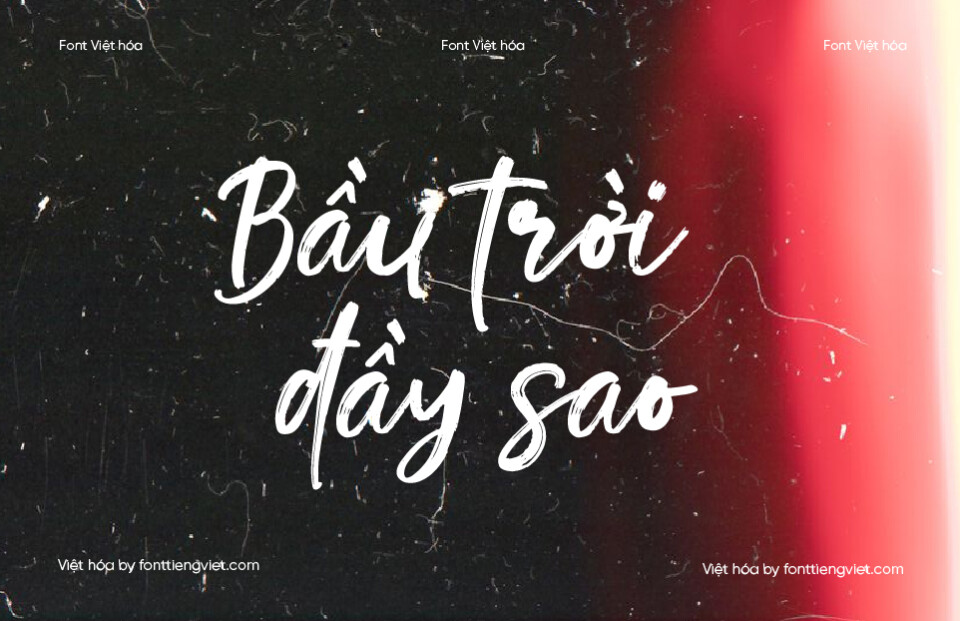
Tải Font Việt hóa 1FTV VIP Doughty Brush: Tuyệt Phẩm Typography Cho Mọi Thiết Kế
Trong thế giới thiết kế đồ họa, việc lựa chọn một Font Chữ phù hợp có thể tạo nên sự khác biệt lớn. Hôm nay, chúng ta sẽ khám phá một “tuyệt phẩm” được cộng đồng designer săn đón: Font Việt hóa 1FTV VIP Doughty Brush. Đây không chỉ là một font cọ nét thông thường, mà còn là sự kết hợp hoàn hảo giữa tính nghệ thuật và khả năng ứng dụng cao, đặc biệt khi đã được Việt hóa. Với sự tỉ mỉ trong từng nét chữ, font này hứa hẹn sẽ là công cụ đắc lực giúp học sinh, sinh viên và các nhà thiết kế tạo ra những ấn phẩm vượt trội, từ đồ án tốt nghiệp cho đến các dự án thương mại.
Khám Phá Sức Hút Đặc Biệt Của Font Việt hóa 1FTV VIP Doughty Brush
Doughty Brush là một kiểu chữ script (chữ viết tay) mang phong cách cọ nét mạnh mẽ và cá tính. Bản gốc của font này đã rất được yêu thích nhờ vào các đường nét tự nhiên, mô phỏng chân thực cảm giác viết bằng cọ mực. Tuy nhiên, đối với người dùng Việt Nam, vấn đề lớn nhất luôn là thiếu ký tự tiếng Việt. Phiên bản 1FTV VIP Doughty Brush đã giải quyết triệt để vấn đề này.
Quá trình “Việt hóa” không chỉ đơn thuần là thêm dấu mà còn là việc tinh chỉnh khoảng cách, kerning và các ký tự đặc biệt (glyphs) để đảm bảo sự liền mạch, hài hòa khi gõ tiếng Việt, từ đó giúp các bạn học sinh, sinh viên dễ dàng tạo ra các bài thuyết trình hay đồ án tốt nghiệp ấn tượng hơn. Sự chuyên nghiệp trong quá trình Việt hóa đã biến Doughty Brush thành một công cụ không thể thiếu trong bộ sưu tập font chữ cao cấp. Chất lượng font chữ này được đánh giá tương đương với các font chữ quốc tế, nhưng lại hoàn toàn tối ưu cho ngôn ngữ mẹ đẻ.
Thiết Kế Đồ Họa Đỉnh Cao Với Phong Cách Brush Art
Font Brush, hay còn gọi là font cọ, là lựa chọn hàng đầu cho những dự án cần sự năng động, sáng tạo và cảm xúc mạnh mẽ. Doughty Brush nổi bật với sự kết hợp giữa nét dày và nét mỏng, tạo ra độ tương phản ấn tượng, thích hợp cho việc thiết kế logo, poster phim, bìa sách hoặc các ấn phẩm quảng cáo. Typography cọ nét này mang lại cảm giác chân thực như một tác phẩm nghệ thuật được vẽ tay, giúp thông điệp truyền tải trở nên gần gũi và cá nhân hơn. Đối với các bạn học sinh chuẩn bị các dự án kỷ yếu hoặc thiết kế áo lớp, việc sử dụng Doughty Brush có thể thổi hồn vào sản phẩm, biến chúng thành những kỷ niệm độc đáo. Font chữ này đặc biệt hữu ích trong các thiết kế liên quan đến nghệ thuật và cảm hứng, nơi mà tính cá nhân được đặt lên hàng đầu.
Tại Sao Font Doughty Brush Việt Hóa Lại Cần Thiết Cho Học Sinh và Sinh Viên?
Để tận dụng tối đa tính năng của Font Việt hóa 1FTV VIP Doughty Brush, bạn cần một số kiến thức cơ bản về phần mềm thiết kế như Adobe Photoshop hoặc Illustrator. Font cọ nét này thường chứa các glyphs (ký tự thay thế) phong phú, cho phép designer tùy chỉnh chữ viết để tạo ra sự khác biệt. Việc khám phá các glyphs này thông qua bảng Character Map sẽ mở ra vô số khả năng sáng tạo, từ việc thay đổi kiểu đầu và cuối chữ cái cho đến việc thêm các nét kéo dài nghệ thuật, làm tăng giá trị thẩm mỹ của sản phẩm cuối cùng.
Cấu Trúc Font và Khả Năng Tương Thích Rộng Rãi
Font Doughty Brush thường được cung cấp ở định dạng OpenType (.otf) hoặc TrueType (.ttf), đảm bảo khả năng tương thích cao với hầu hết các hệ điều hành (Windows, macOS) và các ứng dụng thiết kế phổ biến. Nhờ công nghệ OpenType, các tính năng nâng cao như Ligatures (nối chữ) và Swashes (nét kéo dài) được tích hợp sẵn, làm tăng tính thẩm mỹ và độ chân thực của chữ viết tay mà không cần chỉnh sửa thủ công quá nhiều. Đây là lý do tại sao các font brush chất lượng cao luôn được giới chuyên môn đánh giá cao và được khuyên dùng cho các dự án quan trọng, chẳng hạn như bài dự thi đại học hoặc luận án cao học.